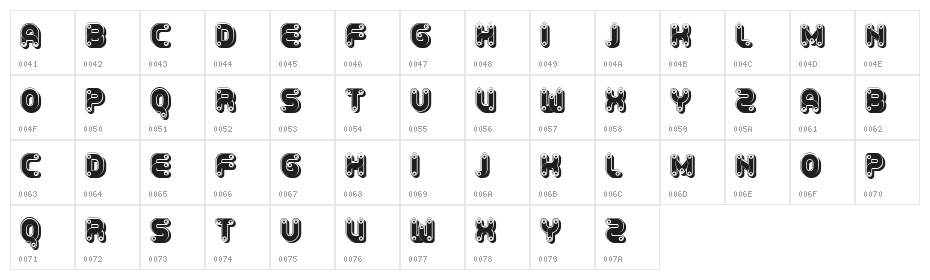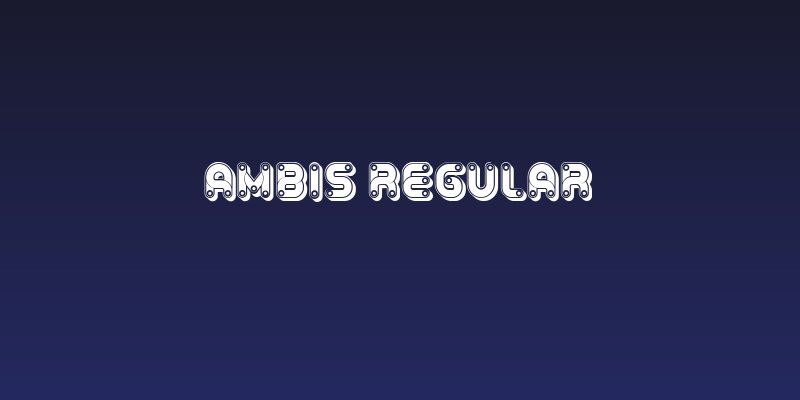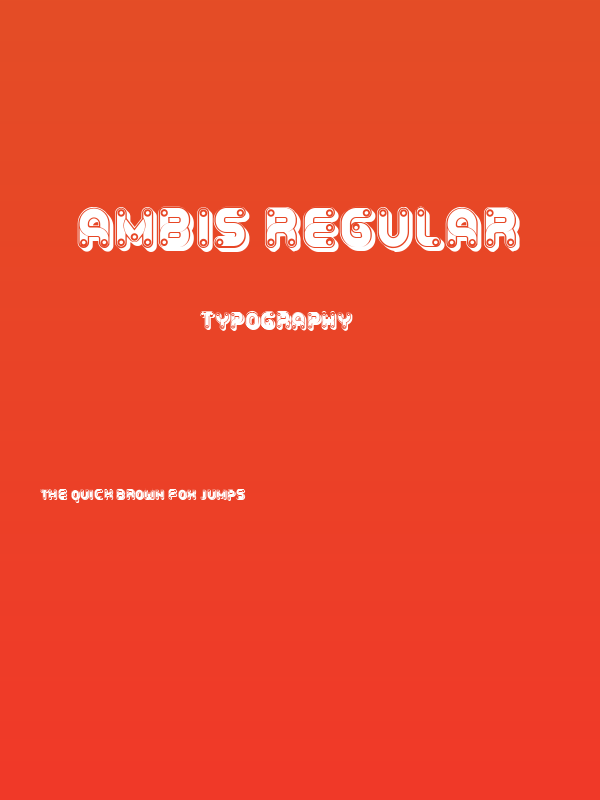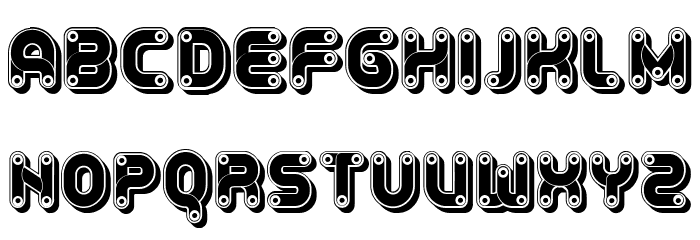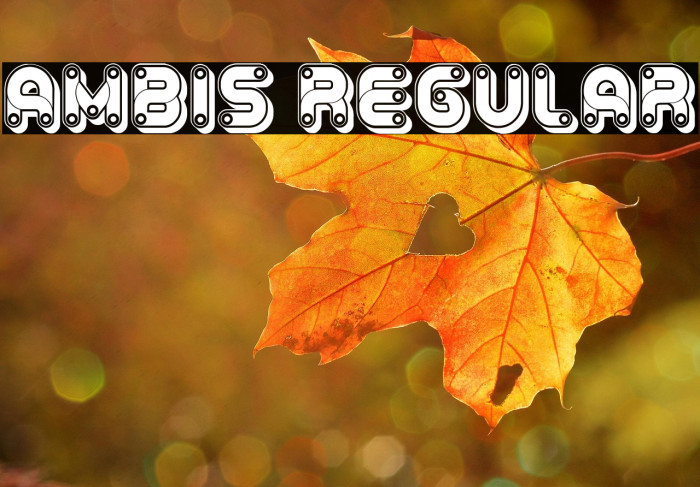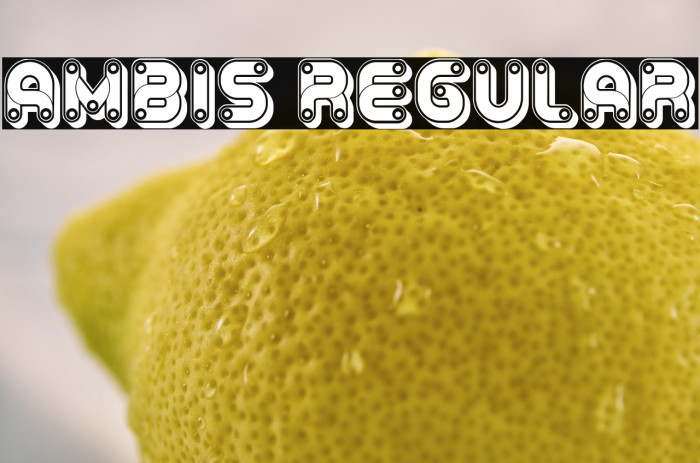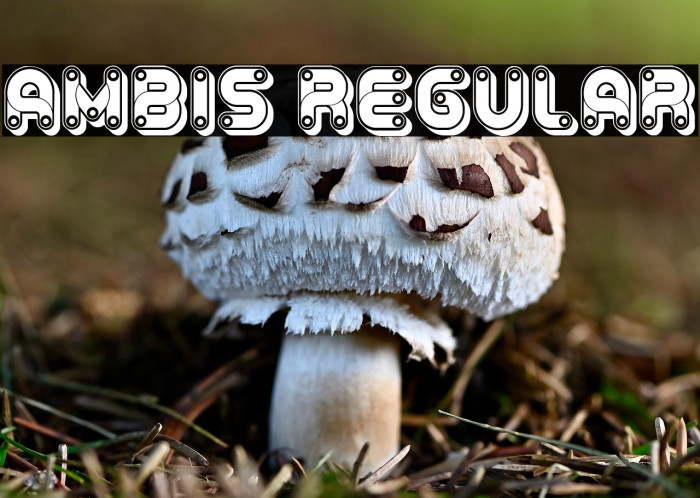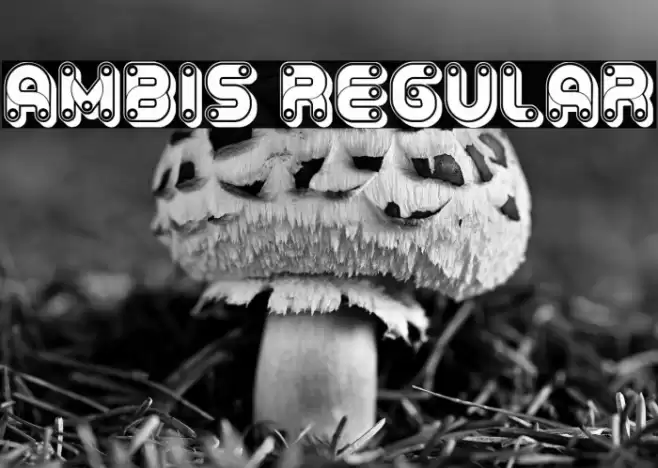
Ambis Regular Font
| Stil general | Modern, Industrial |
| Proiecte propuse | Ideal for technology-themed posters, video game graphics, industrial design branding, and futuristic event invitations. |